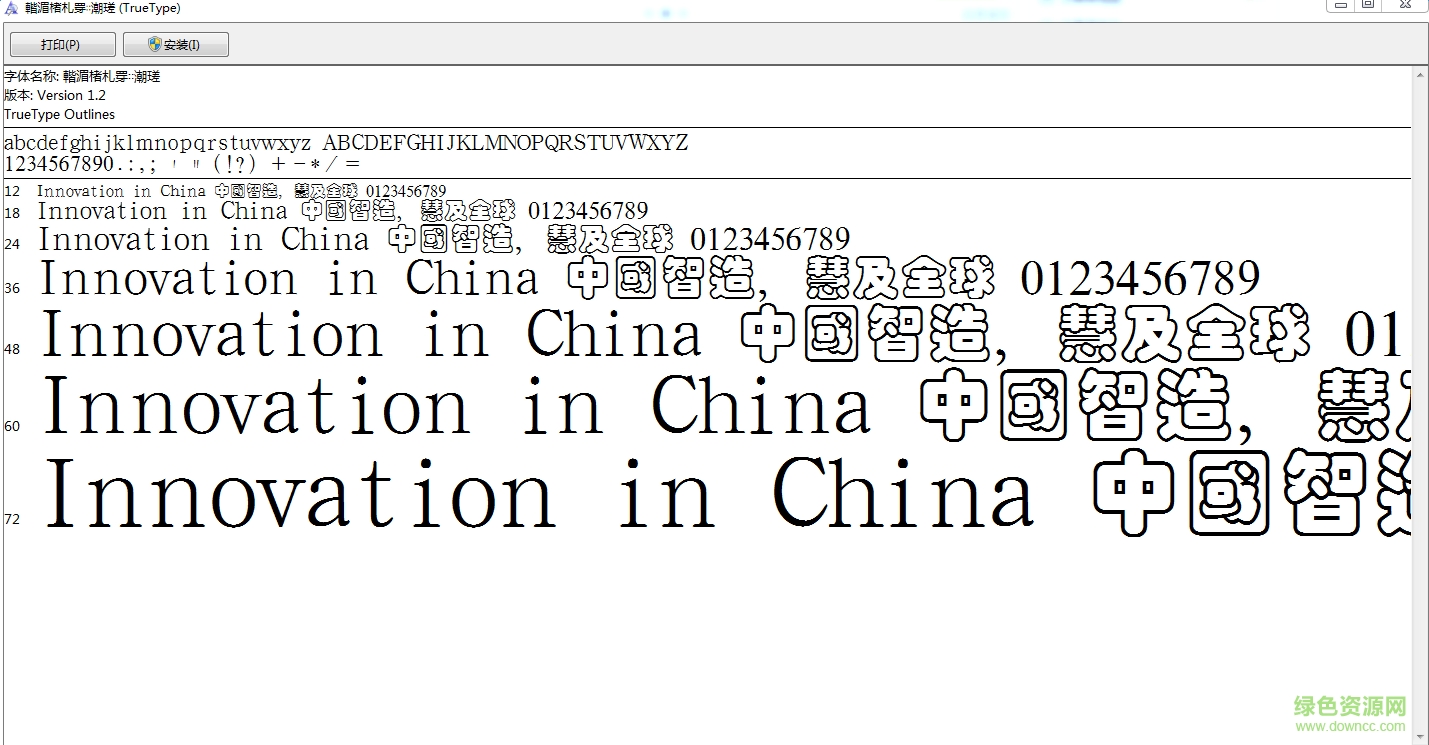
漢鼎繁彩云字體可以用來進(jìn)行平面設(shè)計(jì),在印刷行業(yè)也使用到的比較多。這款字體為漢鼎字體系列繁文字體資源。兼容多種操作系統(tǒng)!需要的用戶歡迎下載使用。
漢鼎繁彩云是一款端正大方的漢鼎字體,字體中間空心,很適合用于海報(bào)、報(bào)紙、ppt等方面的字體設(shè)計(jì),喜歡這款字體的小伙伴快來綠色資源網(wǎng)下載吧!